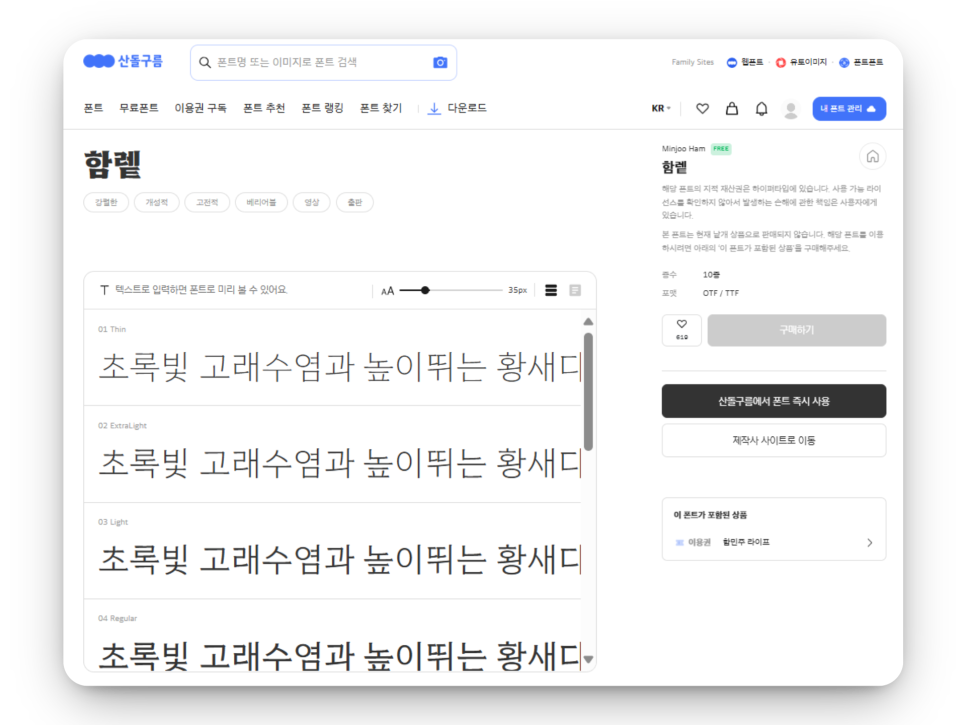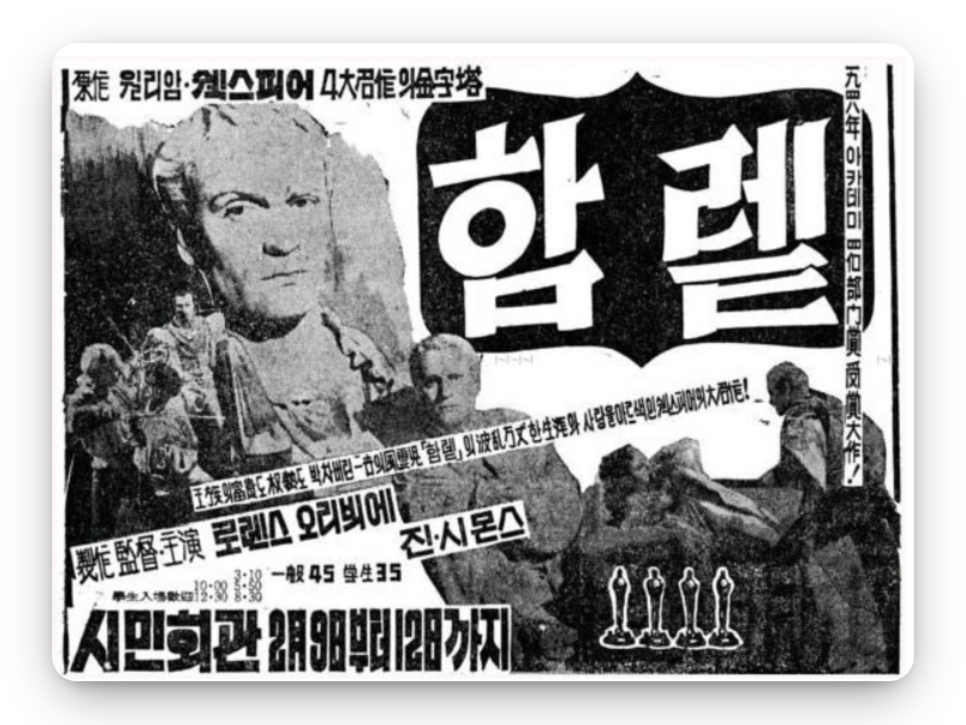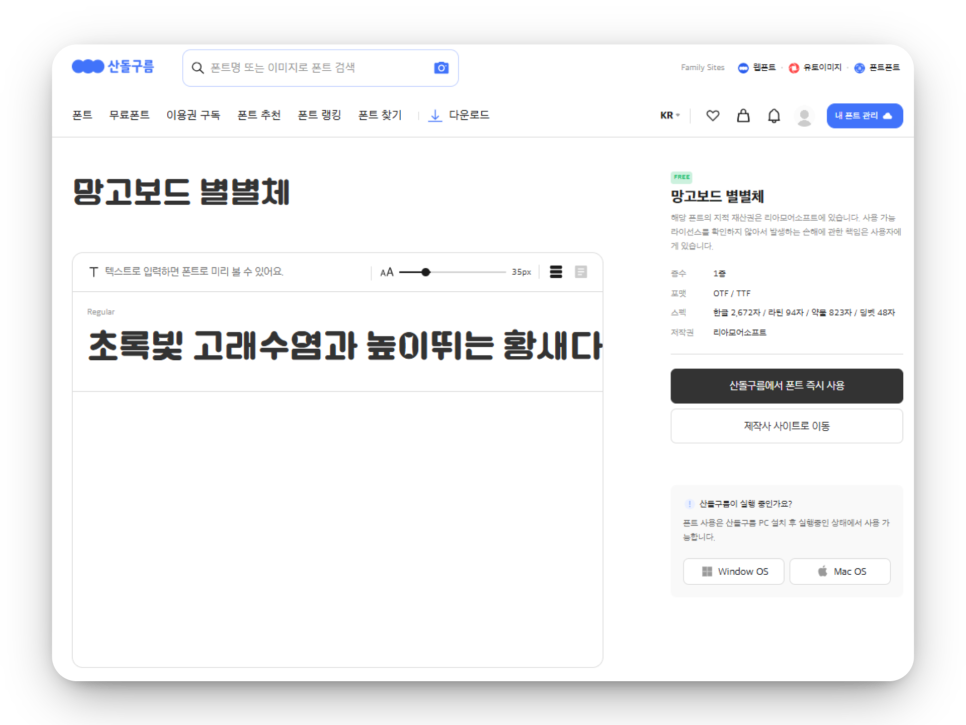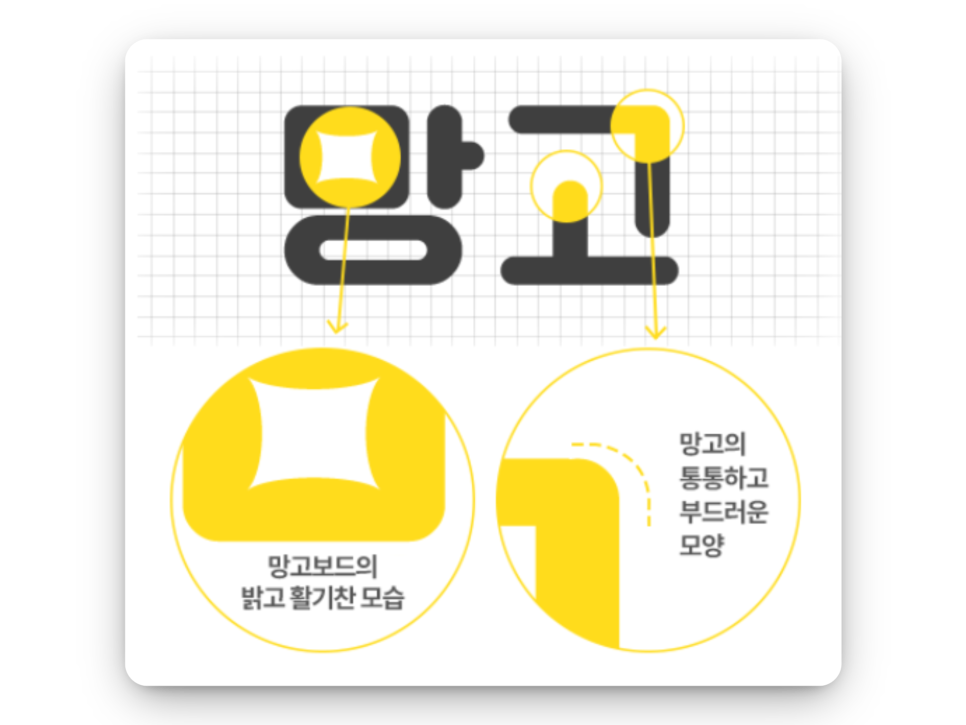
영상 편집을 하다 보면, 자막이 영상 분위기를 결정짓는 경우가 많죠.
오늘은 영상 자막용 무료폰트 3종을 소개합니다.
유튜브나 인스타 릴스, PPT 자막 제작에도
잘 어울리는 한글 글씨체예요.
작은 화면에서도 또렷하게 보이면서,
감각적인 분위기까지 살릴 수 있는
나눔스퀘어 – 안정적인 자막 기본 서체
‘나눔스퀘어’ 미리보기
가장 먼저 소개해드릴 폰트는 '나눔스퀘어'이에요. 문서 본문에도 자주 쓰이지만, 깔끔한 특징과 높은 가독성 덕분에 영상 자막용으로도 활용도가 높습니다.
작은 화면에서도 선명한 무료폰트
글자 끝의 날카로운 부분을 둥글게 처리해 친근하고 부드러운 느낌의 서체예요. 한 가지 서체 안에서 다양한 굵기(weight)를 지원해 제목·본문 자막 모두에 활용할 수 있어요.
추천 활용: 유튜브 인터뷰 자막, 강의 영상, 브이로그 등
함렡 – 복고 감성의 강렬한 인상
무료폰트 ‘함렡' 미리보기
두 번째로 소개할 폰트는 함렡(Hamlet) 폰트예요. 아래 1950년대 한국 영화 포스터 타이틀에서 영감을 받아 제작된 폰트로, 획이 뾰족하고 질감이 살아있어 복고적이면서도 힘 있는 인상을 줍니다.
1950년대 한국 영화 포스터 타이틀
한글과 라틴 문자를 모두 지원하며, 9가지 굵기와 배리어블(Font Weight Axis) 기능을 갖춘 폰트라 텍스트 강조나 타이틀용 자막으로 사용하기 좋아요.
추천 활용: 영화 예고편 자막, 공연 포스터, 영상 오프닝 타이틀
망고보드 별별체 – 포인트 강조용 자막 서체
‘망고보드 별별체' 미리보기
마지막으로 소개할 폰트는 망고보드 별별체입니다. 초성에 별빛 형태의 포인트가 들어가 있어 활기찬 인상을 주며, 문자 폭이 일정해 안정감 있는 구성이라 제목용 자막에 잘 어울립니다.
별빛 포인트가 돋보이는 글씨체
작은 화면에서도 가독성이 높고, 디자인 포인트를 살리면서도 정보 전달이 명확해 영상 썸네일이나 짧은 타이틀 자막에 활용하기 좋아요. 앞서 소개해드린 폰트 2종이 자막용의 깔끔한 서체였다면, 이번 망고보드 별별체로 썸네일에 활용해보는 건 어때요?
추천 활용: 제품 소개 영상, SNS 이벤트 자막, 짧은 타이틀 문구
오늘 소개한 폰트들, 한눈에 비교해 볼까요?
영상 자막에는 가독성과 개성의 균형이 중요합니다.
영상 자막은 물론, 썸네일, 프레젠테이션 등 어디에나 잘 어울려요.